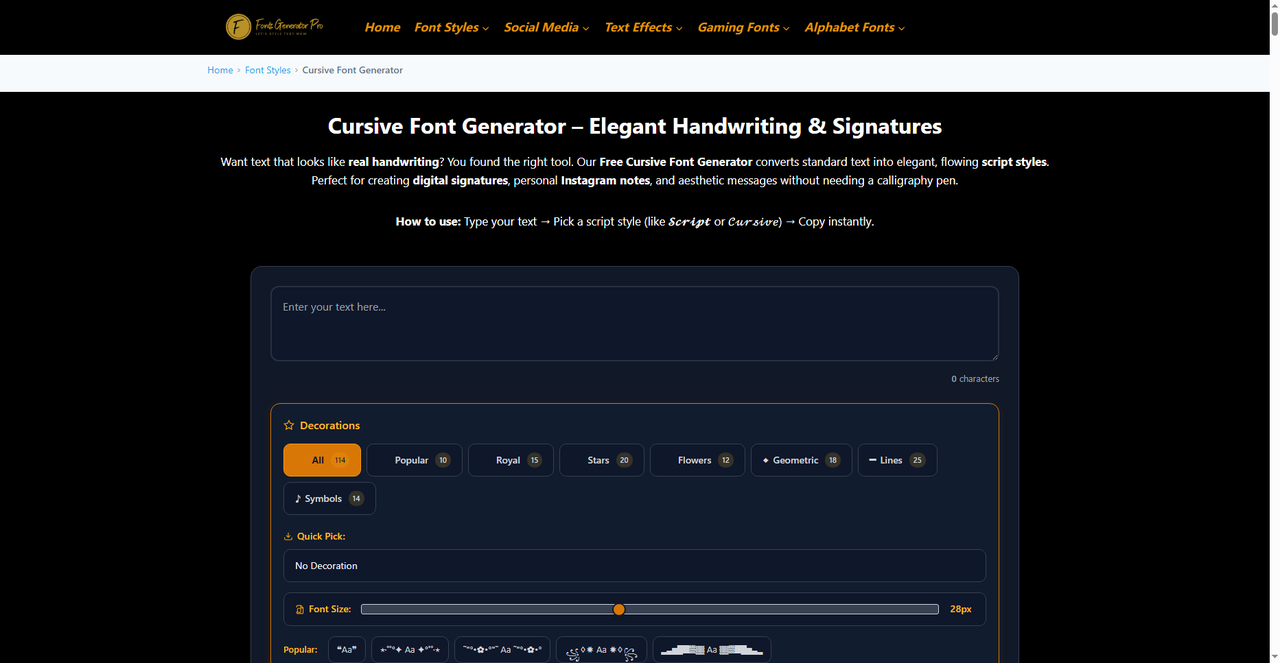
艺术签名一键生成体验,商务和个性风格都有
签合同、发邮件、做个人品牌视觉,不少场合都需要一个拿得出手的签名。但字迹因人而异,不是每个人都写得满意,而且电子文档里也没法直接手写。找设计师定制一个签名成本不低,动则几十上百,还不一定能一次到位。用在线工具自己生成一个风格合适的签名,试错成本低、速度快,是很多人都会主动考虑的解决方案。现在签名生成工具种类不少,从电子合同用的功能性签名到社交媒体用的装饰性花体字,各有各的适用场景。
字由本身不是专门的签名工具,但它在中文签名这个场景下的实用性很强,核心原因是字体库里的书法和手写资源足够丰富。客户端打开后,上方筛选栏可以直接定位到书法和手写两个大类,隶行草楷下面各有多个细分标签,商务场合偏好的端庄楷书、个人表达常用的行草、甚至偏艺术感的篆书都能找到。光是书法体就有几十款,手写体数量更多,覆盖了从工整到飘逸的多种审美取向。需要长期使用、希望在多款字体之间反复做比较的人,这个资源量完全够用。
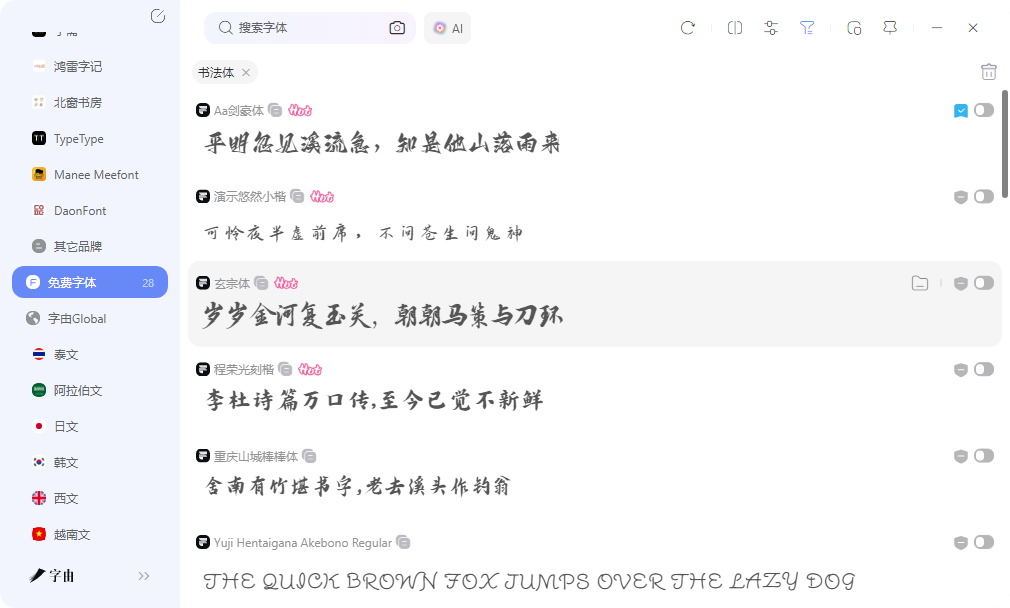
预览框是实际选字时用得最多的功能。输入自己的名字、品牌名或者常用署名,不同字体的效果直接并排对比,字号能放大缩小,颜色也能换,不用先激活到系统里就能看到最终感觉。这个过程不消耗任何额度,反复试多少款都没关系,选中了再一键激活,字体才会真正进入使用状态,没选中的不会在系统里留任何痕迹。对签名这种需要精挑细选的场景来说,能提前看到完整效果再做决定,省了不少来回折腾的时间,也不用担心系统里堆积大量不用的字体文件。
2、Fonts Generator Pro
Fonts Generator Pro在基础字体转换之上增加了装饰元素功能,走的是视觉增强路线。除了常规的草书和手写体外,还整理了星星、花卉、几何线条、音乐符号等上百种装饰边框,可以给签名加上皇冠、闪光、藤蔓等各类视觉效果。字号支持自由调节,从细小的注释到醒目的标题都能满足。生成结果复制即用,适合需要视觉吸引力的社交媒体场景。装饰元素虽然丰富,但建议适度添加,过多会影响文字辨识度,反而达不到签名的效果。对于做自媒体封面、个人主页头图、活动海报这种需要吸睛的场景,这个工具的发挥空间比较大,能做出辨识度很高的视觉效果。
3、Online Fonts Generator
Online Fonts Generator专注草书和花体字转换,在英文签名的风格化方向上做得比较深入。输入任意文字后,页面会即时输出几十种手写风格的变体,从优雅连笔到装饰性较强的花体都有,可选数量很可观,风格跨度也大。生成结果可以直接复制使用,粘贴到社交媒体个人简介、邮件签名或者聊天工具里都能正常显示,不会出现乱码。整个过程不需要下载文件,也不需要等待加载,输入的同时就能看到全部效果,响应速度很快。对想要英文签名的用户来说,操作流畅度和可选范围都令人满意,拿来应急或者日常使用都够用了,做品牌推广、自媒体运营的时候也能派上用场。
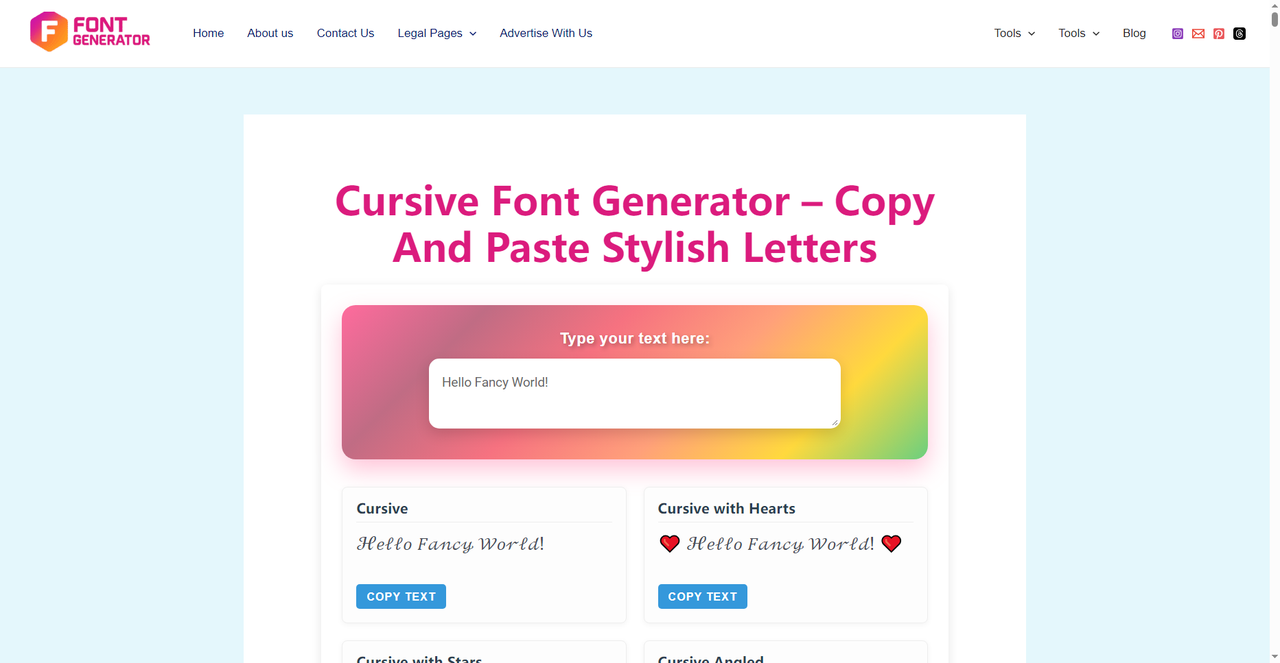
4、Otto
Otto的签名生成器和Signaturely在功能结构上比较接近,同样支持手绘和文字输入两种方式。它的特点是打开就能用,不需要注册账号,也不用绑定邮箱,对于不想留个人信息的用户来说比较友好。文字模式下有十多种字体风格可选,正式的商务衬线字体和流畅的手写体都有涵盖,商务和个人场景都能兼顾。生成后的签名可以直接复制或下载,用于邮件签名档、文档审批、表单签署都比较顺手。页面里还附带了一些关于签名性格分析的趣味内容,从笔迹倾斜度、连笔方式等角度做一些解读,虽然不算严谨科学,当作参考看看也还行,能给自己选风格时多一些思路。
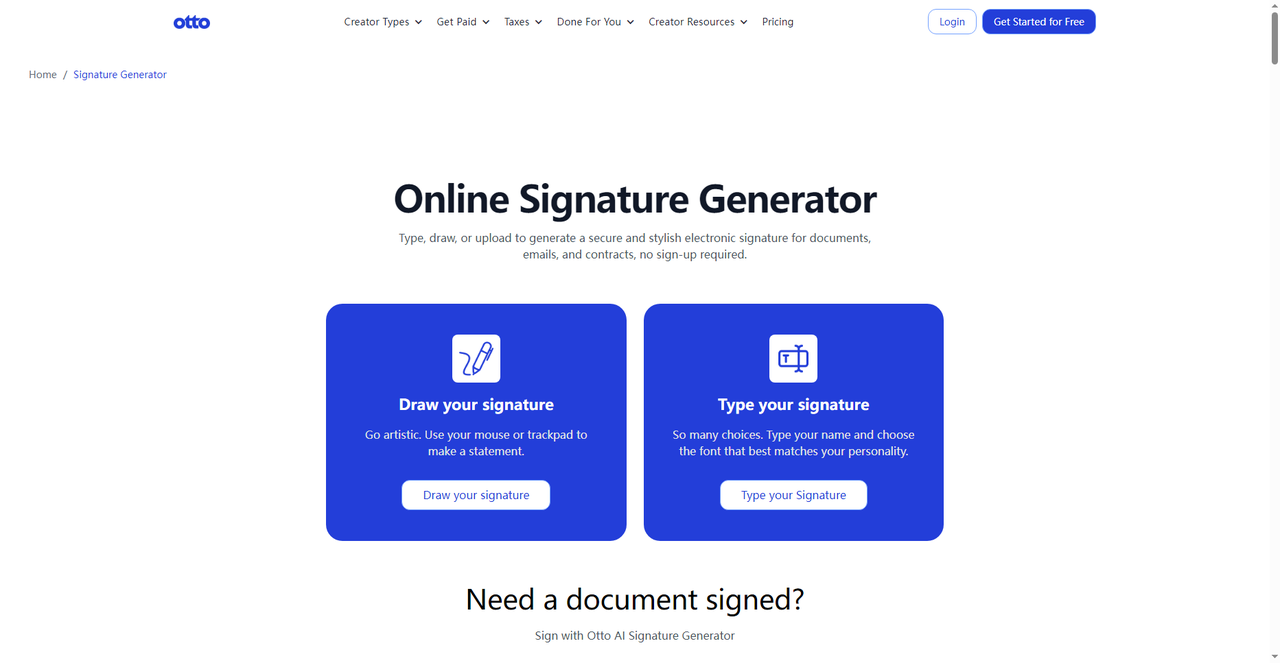
5、Signaturely
Signaturely的签名生成页面设计得很清爽,进来就是两个选项:手绘签名和文字签名,选择路径很明确。手绘模式用鼠标或触控板直接画,画完可以调整线条粗细和颜色,适合想保留手写触感的人,缺点是鼠标画的精细度有限,用触控板或数位板体验会更好。文字模式则高效得多,输入姓名后从多种字体中挑选,系统实时显示效果,衬线体、手写体、花体都有涵盖。所有签名都可以免费下载PNG格式,透明背景,直接插入Word、PDF或者其他文档里就能用,不需要额外处理背景。这个工具的定位偏向正式电子签名,生成结果可用于合同、协议等商务文档,网站也对电子签名的法律效力做了详细说明,有合规需求的用户可以重点看看这部分内容。
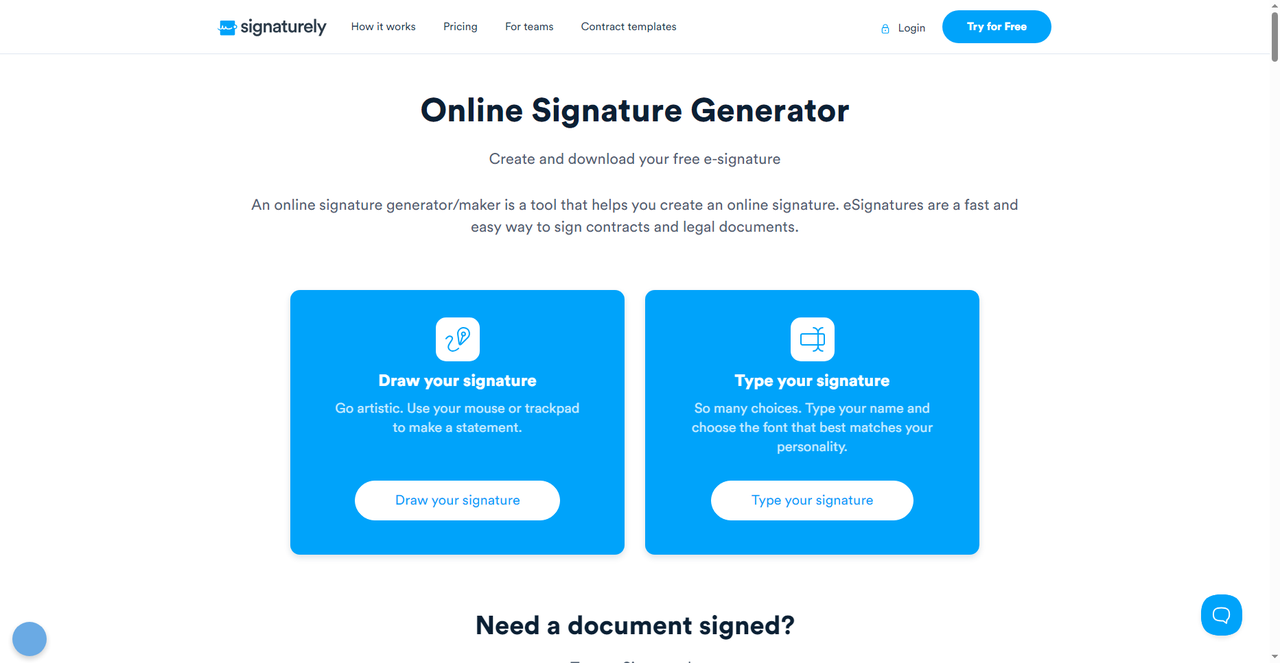
五种工具的定位差异比较明显,选的时候先看自己的主要需求是什么。字由胜在中文字体资源深度和AI辅助能力,适合对中文签名有较高要求、愿意花时间反复调试的用户。Signaturely和Otto更偏向功能性的电子签名生成,前者文档集成度和法律效力说明更完善,后者使用门槛更低、隐私性更好。Online Fonts Generator和Fonts Generator Pro则聚焦英文签名的风格转换,前者胜在速度和选择面广,后者在装饰性和视觉冲击力上有更多玩法。根据具体的使用场景和语言需求来挑选,效率会更高,也不至于花了时间才发现工具不匹配。